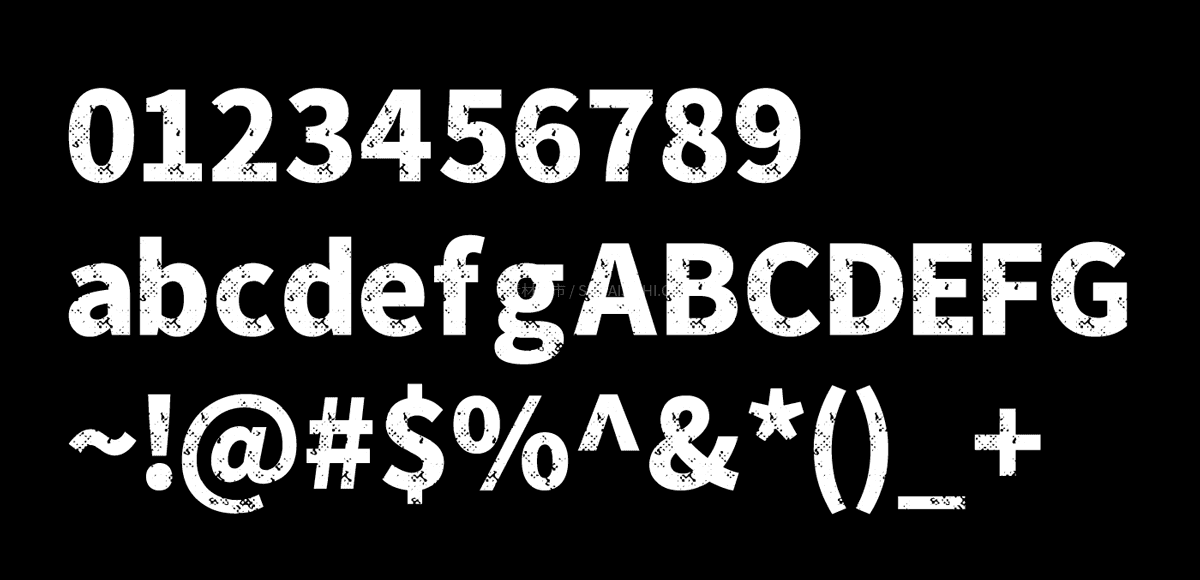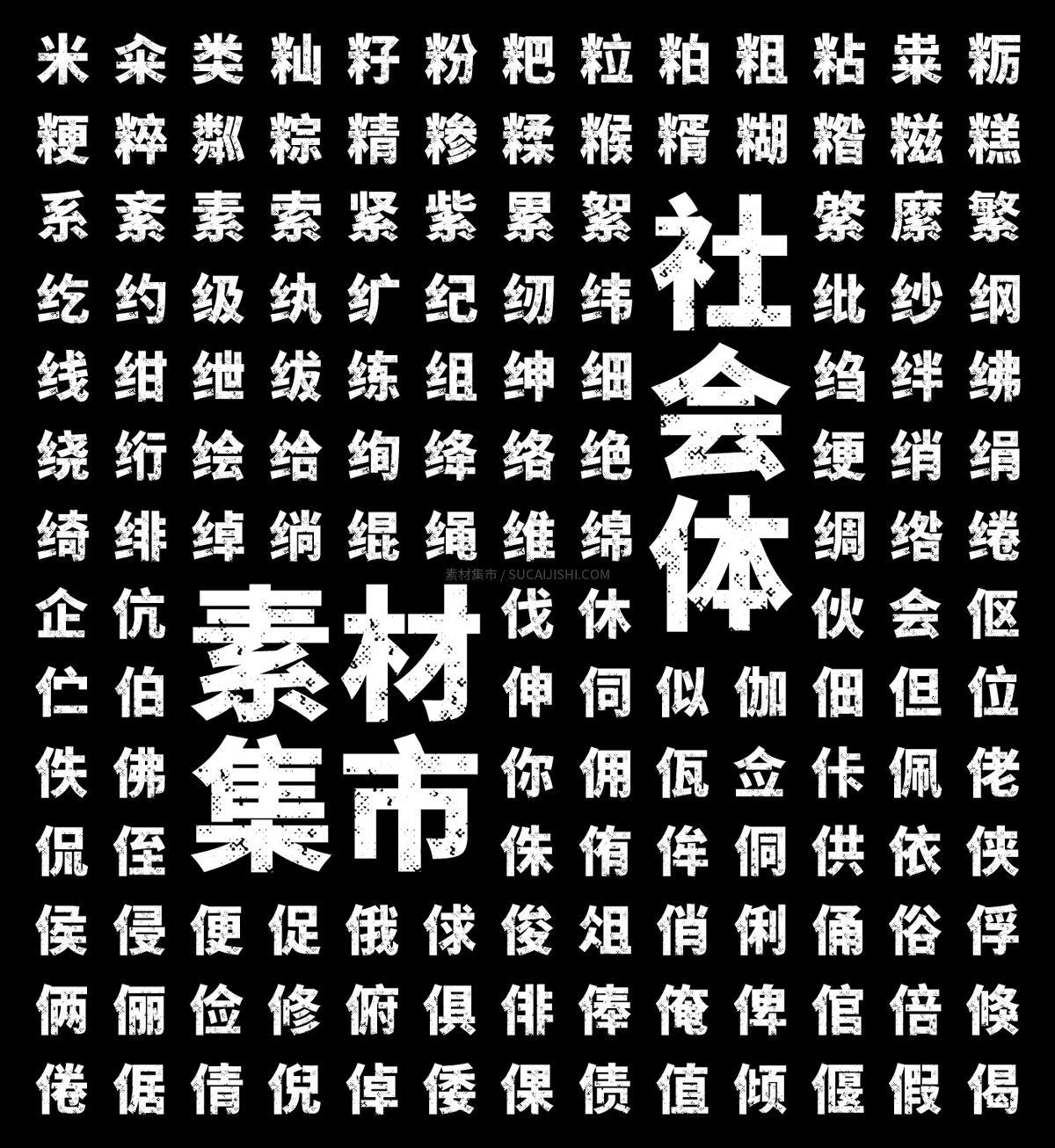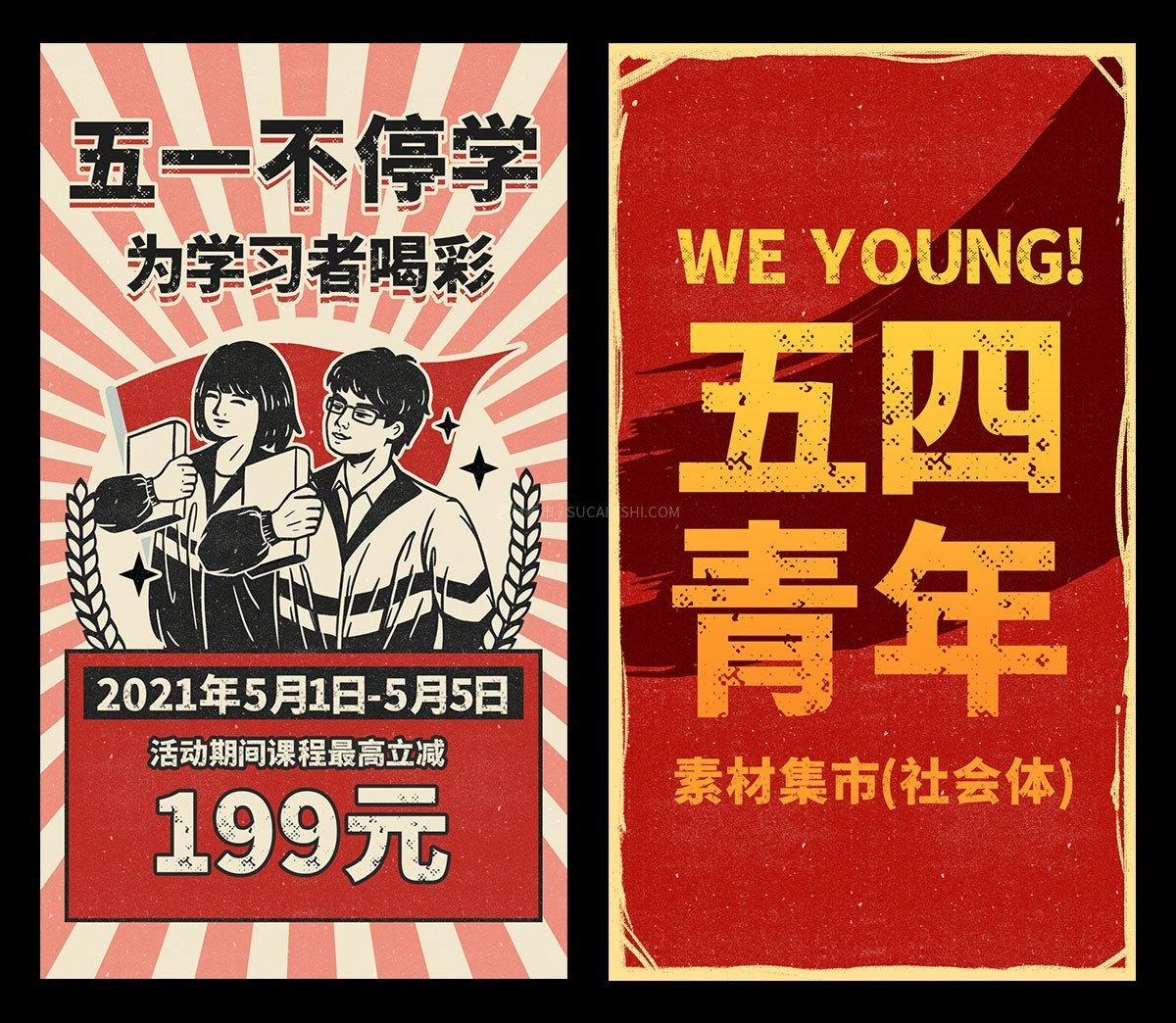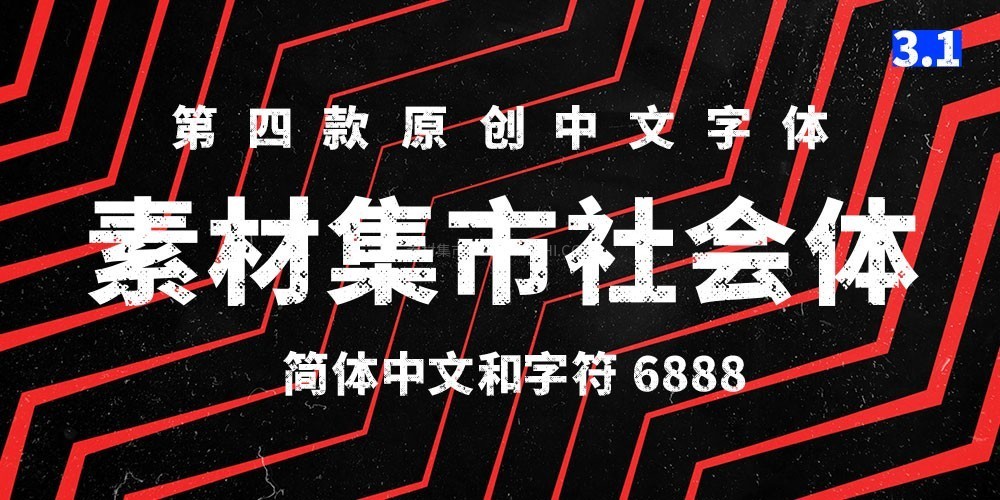
素材集市社会体是一款基于思源黑体 – Black 改造而成的主打复古怀旧、破旧斑驳风格的免费商用中文字体,由 10 位来自不同行业的设计师历时 4 个月联合制作完成。
设计上,保留了思源黑体 – Black 原本方正、识别度高的字形骨架,在笔画上添加了磨损、污渍、颗粒、断裂等旧纹理,模拟出一种街头涂鸦、老海报、印刷瑕疵的复古视觉效果。
字符集涵盖 GB2312 编码标准的 6763 个简体中文,加上英文、数字和符号共 6888 个字符。由于是开源字库思源黑体的衍生字体,所以也同样遵循 SIL OFL 1.1 开源协议,无论是个人还是企业都可以免费商用。